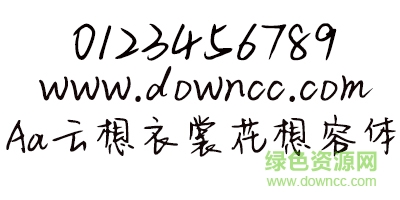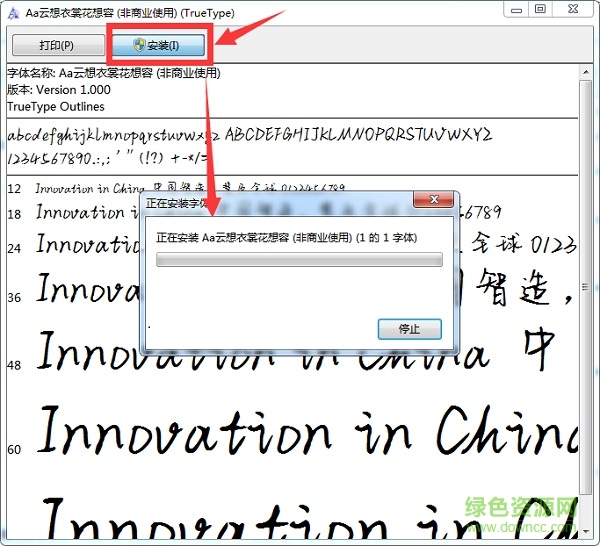
云想衣裳花想容體ttf是一個(gè)外形行云流水的藝術(shù)字體。這款字體支持簡體中文、英文以及數(shù)字輸入。在設(shè)計(jì)行業(yè)很受歡迎!如果你也喜歡的話,就來本站免費(fèi)下載吧。
云想衣裳花想容字體是由Aa字庫全新制作的一款文藝字體,字體充滿了詩情畫意,筆畫看上去也是非常的飄逸!這款字體使用的范圍也是非常廣泛。有需要的用戶快來綠色資源網(wǎng)下載安裝吧。